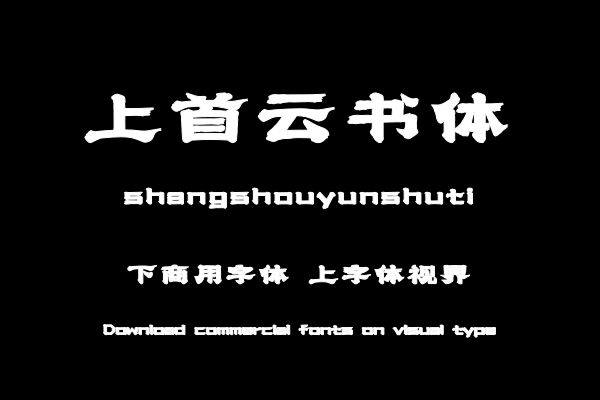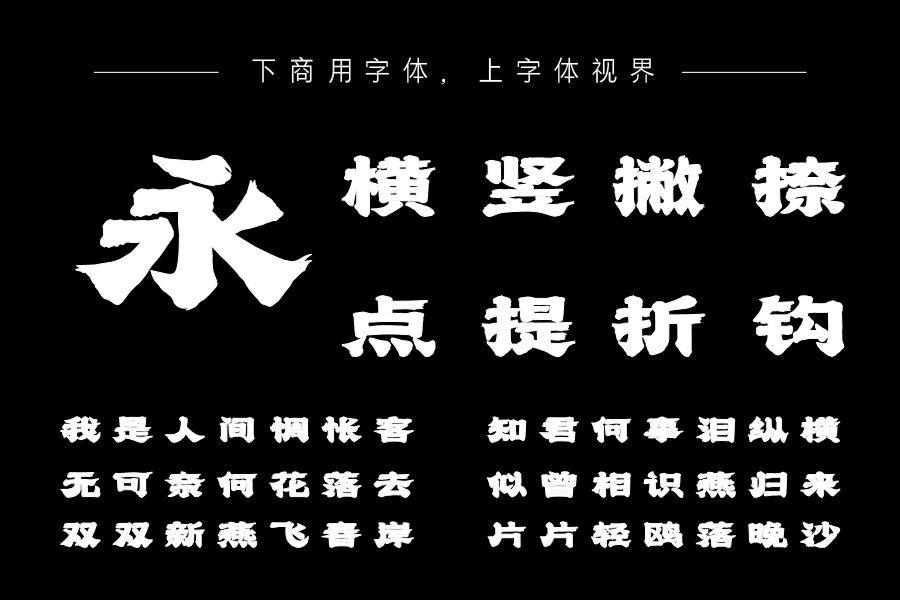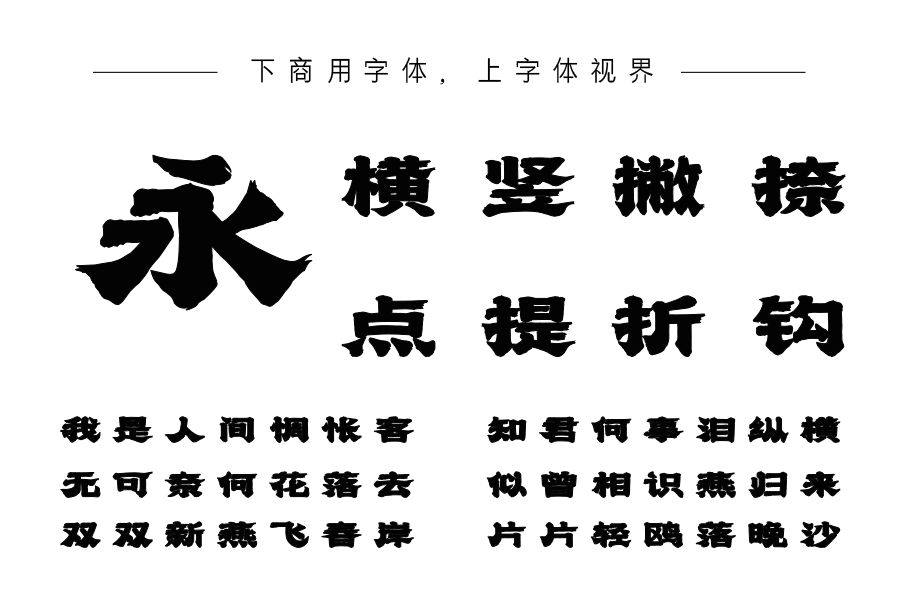
上首云书体,本套字体风格偏手写,在视觉呈现上给人一种沉稳秀丽的感觉,在本套字体笔画设计上,笔画不规则且有一定弧度的毛笔笔触感,使字体看着比较刚劲优雅。整套字体在......购买须知:“下载服务费”与“字体VIP”所获得字体 仅用于个人非商用, 商用请联系付费授权。本字体为电脑用字,手机没有root权限不支持直接手机换字(手机如何root,请自行百度搜索教程)。购买前请先 了解清楚后再付款 ,字体为虚拟产品无法回收 一旦购买不支持退款。